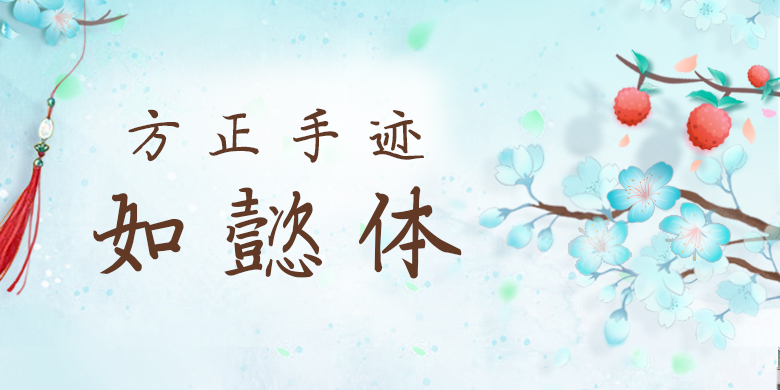
方正手迹-如懿体 品牌: 方正手迹 设计师: 潘小桥 发行时间:2020 字库编码:大陆简体(GB2312-80) 分类:常规书写·硬笔 字体属性:心动字 中国风手写古典优雅楷体标题正文杂志书籍广告影视电商海报包装新媒体综艺游戏 如懿体结字中正大气,结构严谨,用笔从容不迫,娓娓道来。书法气息浓郁,作者创造性的在传统小楷的基础上加入现代书法气质,符合当今的大众审美。适用于现代诗歌、短文的排版以及文化、商业类品牌的广告语设计。 字体下载地址 官方下载